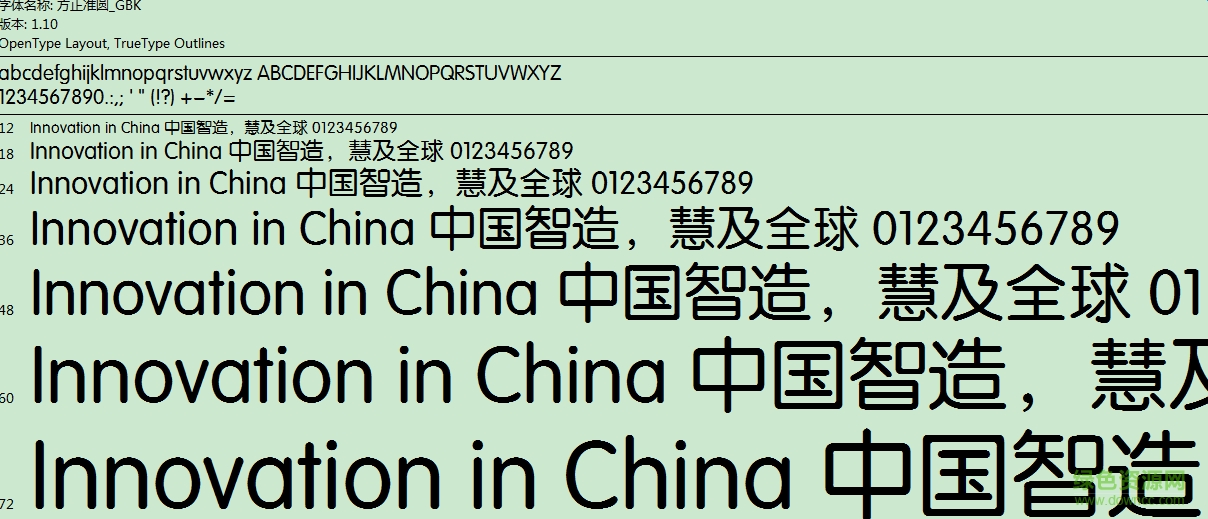
fzy4k gbk1 0是一款非常漂亮的字體,這款字體的用途也是非常的廣泛哦,各種廣告設(shè)計和印刷都會用到的,有需要的朋友就來綠色資源網(wǎng)下載體驗吧!
fzy4k(方正準圓)這是一款非常優(yōu)秀的字體應(yīng)用軟件,該款字體設(shè)計十分的出色,可以給文字編輯工作使用,高端的氣質(zhì),更加適合傳達文字表達的意思!